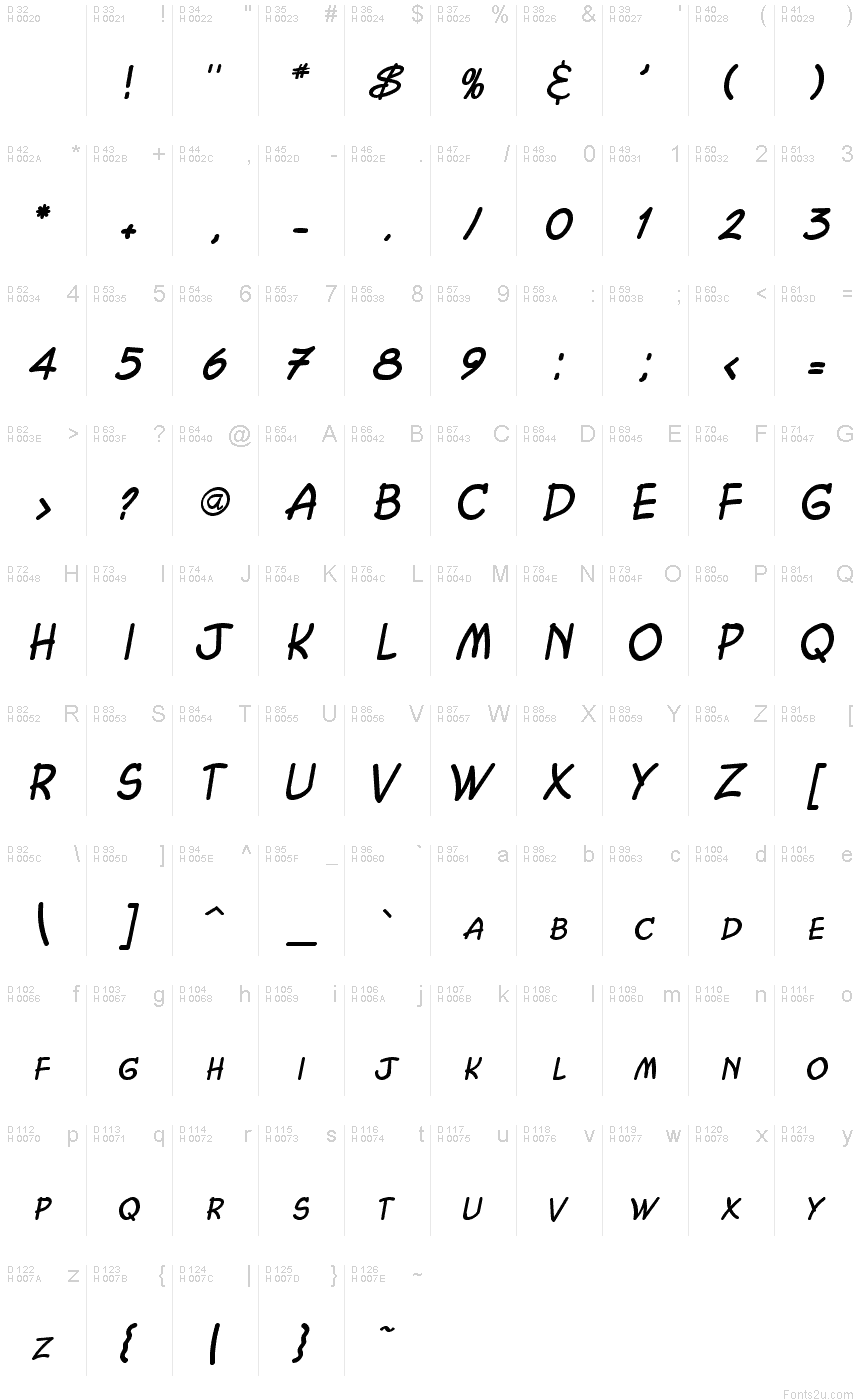
Chasm Italic di Bay Animation Inc. è un carattere tipografico gratuito in stile fumetto, caratterizzato da un ritmo vivace e sciolto e da tratti che ricordano l'uso di un pennarello. Le lettere si inclinano in avanti con naturalezza, conferendo ai titoli un'energia disegnata a mano: un aspetto amichevole ma abbastanza audace da catturare l'attenzione.
Usa Chasm Italic per dare personalità a titoli di fumetti, copertine di libri per bambini, loghi giocosi, anteprime per YouTube, biglietti d'auguri e adesivi. Le curve generose e il corpo robusto mantengono la leggibilità anche in dimensioni ridotte, mentre l'inclinazione informale rende tutto più vivace. Per un abbinamento semplice, usa Chasm Italic per i titoli e accompagnala con un carattere sans serif geometrico e pulito per il testo principale, così da dare un tocco equilibrato a questo look divertente.